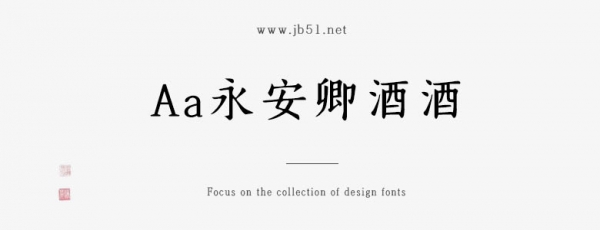
Aa永安卿酒酒是一款不錯(cuò)的藝術(shù)字體,由Aa字庫(kù)出品,字體筆觸適中,字形端正,擁有字符數(shù)8028和字形數(shù)8183,具有很好的視覺(jué)感,適合應(yīng)用于藝術(shù)設(shè)計(jì)、平面宣傳設(shè)計(jì)、網(wǎng)頁(yè)設(shè)計(jì),書(shū)法字帖等領(lǐng)域,需要的朋友可以前來(lái)本站下載。